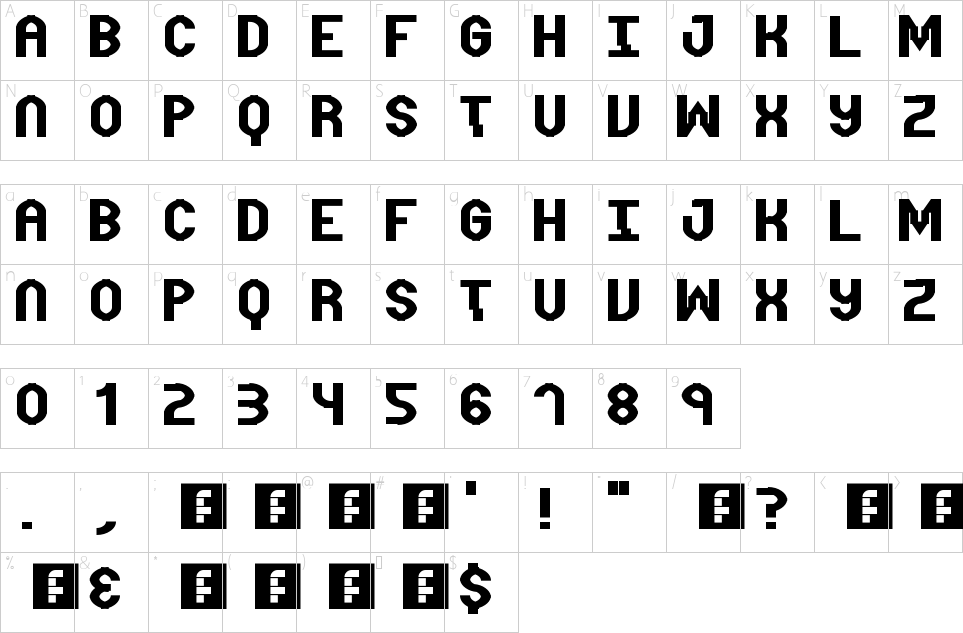
Aqui está uma descrição para a página de download da font ‘Distortion Font’, mantendo os requisitos fornecidos: A Distortion é uma fonte criada pelo designer Geronimo Fonts e disponível gratuitamente tanto para Windows quanto para Mac. Desenvolvida com um toque único, essa fonte traz ao seu design gráfico algo de distorcido e inusitado que pode tornar seus projetos ainda mais atrativos e distintivos. Com 4.140 downloads já realizados, a Distortion é uma opção confiável para quem procura adicionar um toque diferente em suas criações digitais. Seja você um designer de sites ou gráficos profissionais, essa font pode ser sua perfeita companheira para dar vida à suas idéias e projetos digitais inovadores.